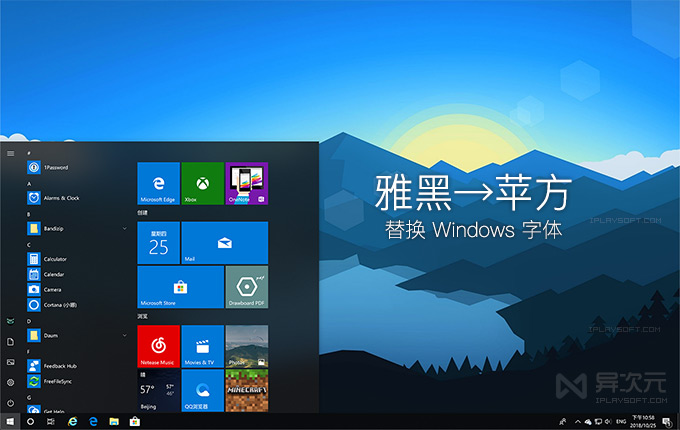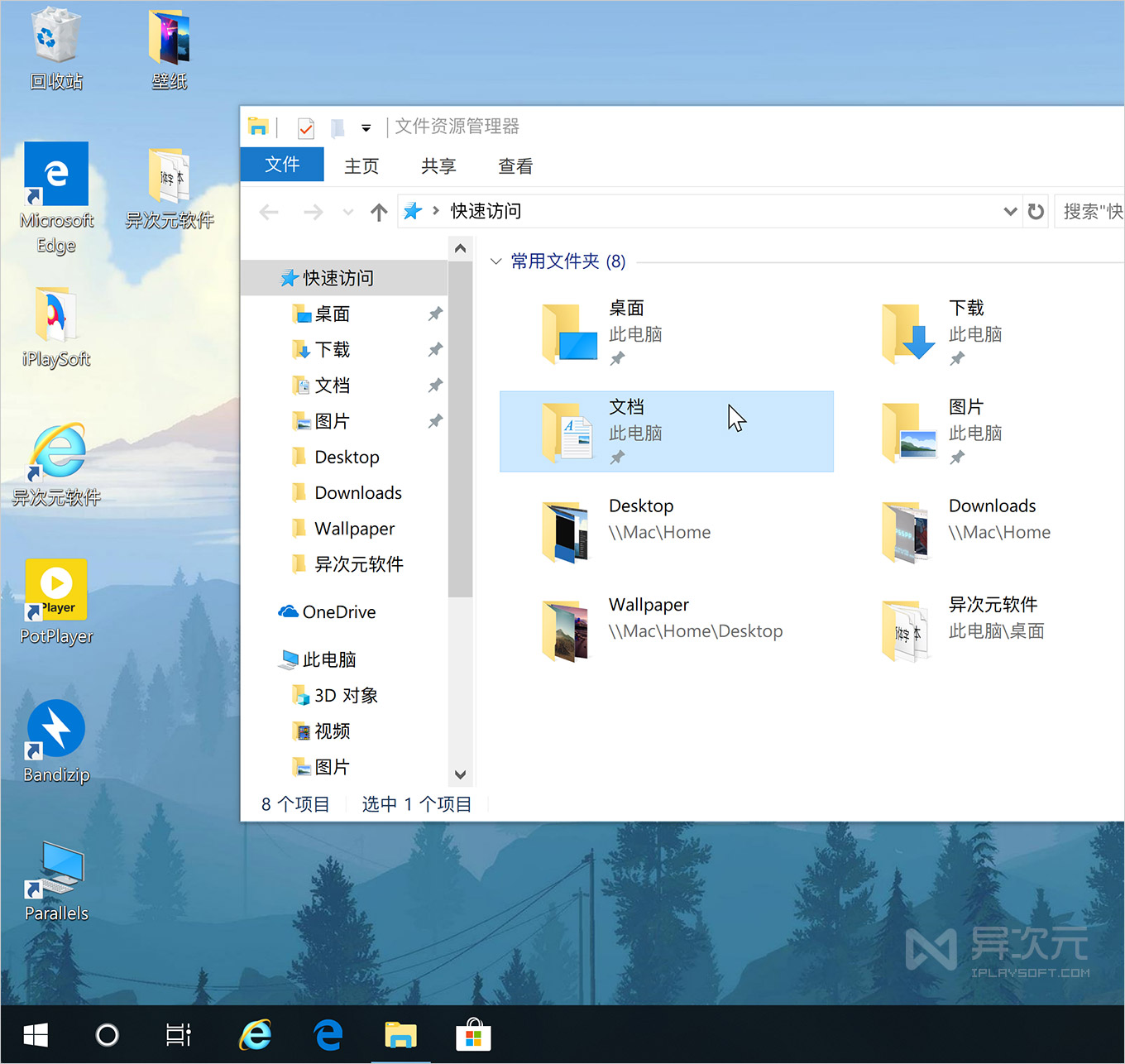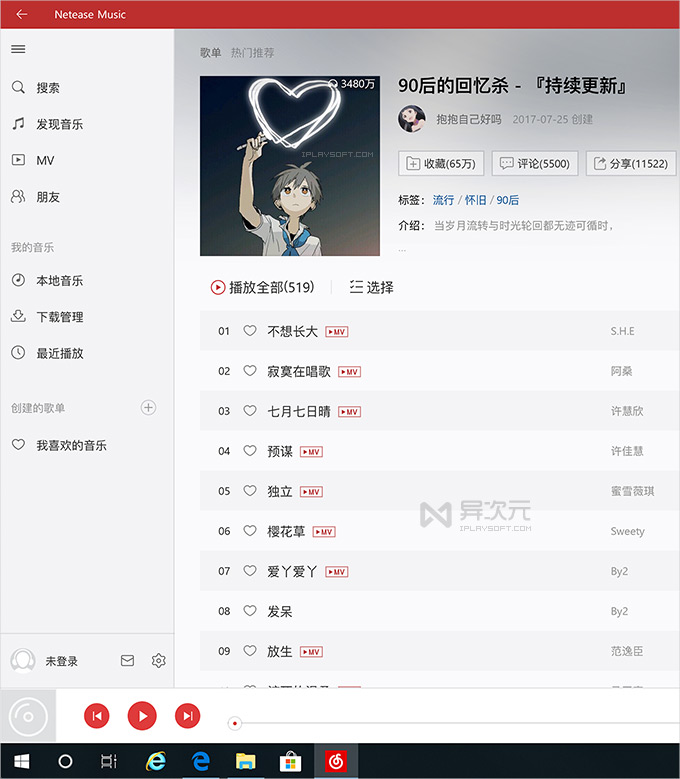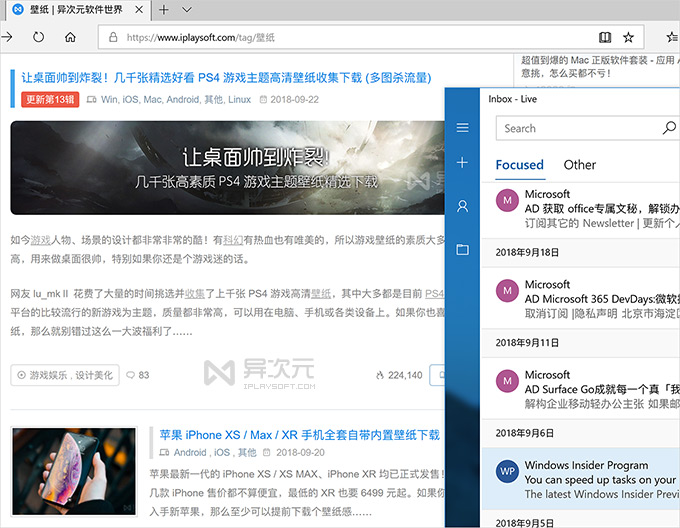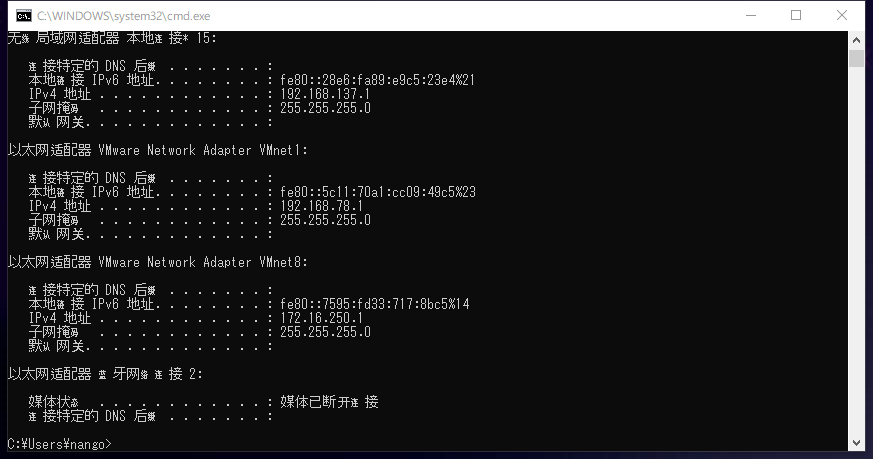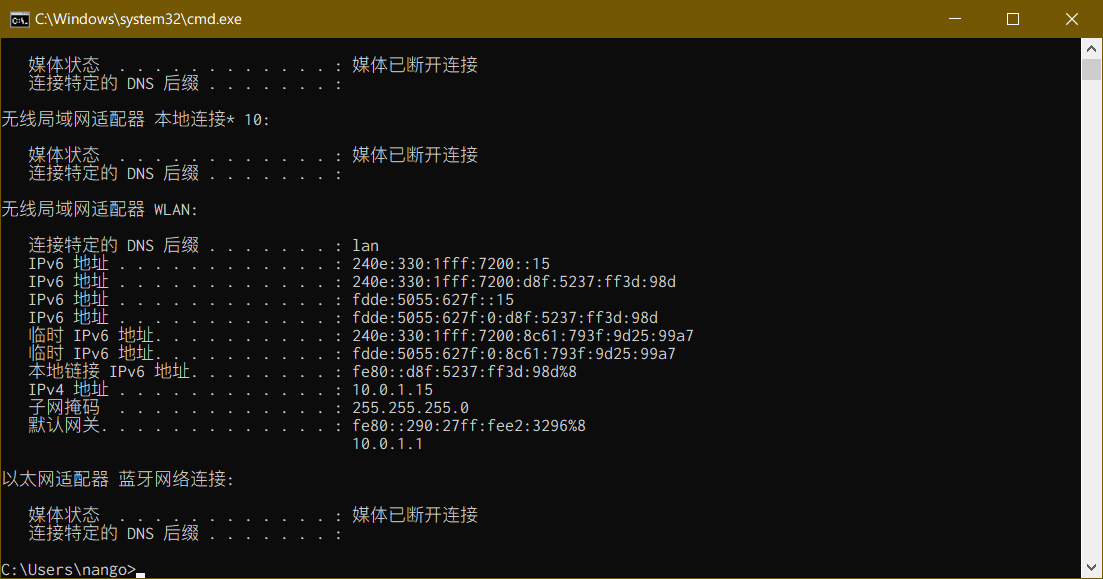
Win10 系统替换 macOS 苹方字体 – 瞬间提升文字清晰度与显示渲染效果
微软雅黑字体最早出现在 Windows Vista 时代,尽管它设计很经典,但由于当时并未充分考虑高分辨率屏幕的优化,如今在 4K 高清屏下字体显示效果比隔壁苹果的 macOS 还是差一截。
为了让字体显示更加清晰锐利,微软在最近的 Windows 10 Insider 内测版中“重绘了”雅黑字体。这个改动颇受好评,用户们十分感动!然后微软在正式版中顺手就将这个改动砍掉了……砍掉了……砍掉了……嗯,既然这样,咱们还是自己动手来改善字体的显示效果吧……
Win10 替换苹方字体,让清晰度和观感大幅提升!
由于苹果 Macbook 几乎全系标配超高清的视网膜屏,所以 macOS 自带的「苹方字体」可以说天生就是为高分屏而设计的!在 2K、4K 甚至更高的分辨率下显示效果拔群!那么,如果将 Win10 的系统默认字体替换成苹方,自然就能获得相当不错的高清字体渲染效果了。
网上已有不少网友实践过,确实能获得大幅的观感提升 (主要是更清晰锐利)。而我们要做的事情也很简单,就是用苹方字体替换掉 Win10 自带的 雅黑 和 宋体 两种字体。而且此方式可以随时还原,所以也无须担心系统稳定性和安全性。
值得注意的是,由于苹果字体渲染方式是为「高分屏」而设计的,只适合高 PPI 的显示器 (粗略判断:Win10 默认的推荐缩放比例大于等于 125% 才算是高分屏),在低分辨率屏幕下「并不」建议替换,渲染出来反而会发虚,效果还不如雅黑。但如果你正在使用 4K 显示器 或者 4K 电视,那么就比较值得一试了。
Windows 10 系统使用苹方字体效果图:
咱们先来看看 Windows 10 在更换萍方字体后的实际显示效果如何吧。不过由于下面的截图尺寸较小,难以体现出真实效果,实际上在大屏幕上看到的观感差异还是比较大的,个人认为比起雅黑,苹方会更加细腻舒适。大家可以感受一下:
由于本文提供的苹方字体已自带了 macOS 的字体渲染效果,所以你不需要额外安装和使用其他渲染软件,替换雅黑和宋体后即可达到全局接近 macOS 系统般的字体显示效果。
当然,用同样的方法处理,理应也可以将 Windows 替换成其他字体,比如思源黑体、思源宋体、小米兰亭等。不过美观程度有没有苹果的字体好看就见仁见智了。而且观感清晰度什么的也只能试过才知道,有兴趣的朋友不妨试试看还有没更适合 Windows 的中文字体吧。
使用原有苹方字体效果
使用大佬修改后的效果